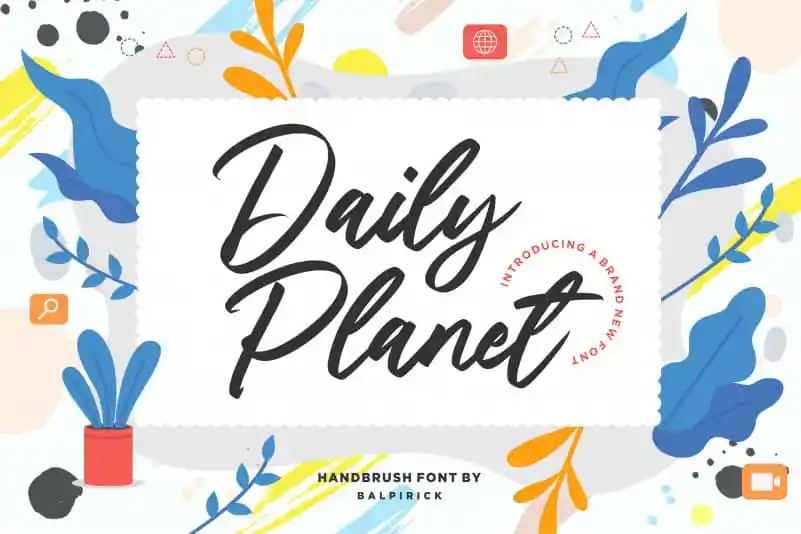
Daily Planet Handbrush Font – Download Grátis
A Daily Planet Handbrush Font é uma escolha perfeita para quem busca uma mistura única de modernidade e autenticidade nas aplicações digitais. Ideal para uso em nomes de lojas, logotipos e banners, esta tipografia é um blend entre design gráfico contemporâneo e arte manual. Seja você criando embalagens de produtos ou projetando uma nova marca, a Daily Planet Handbrush Font trará um toque distintivo à sua identidade visual. É especialmente adequada para aplicações em revistas, redes sociais e qualquer lugar onde deseje destacar os textos acima do fundo. Além disso, ela também é perfeita para usar de forma criativa no marketing digital e nas redes sociais para criar um impacto imediato e pessoal que ressalta a personalidade da sua marca ou projeto. Com seu designer habilidoso balpirick, esteha fonte se torna uma ferramenta indispensável para quem busca aprimorar suas habilidades de design gráfico.